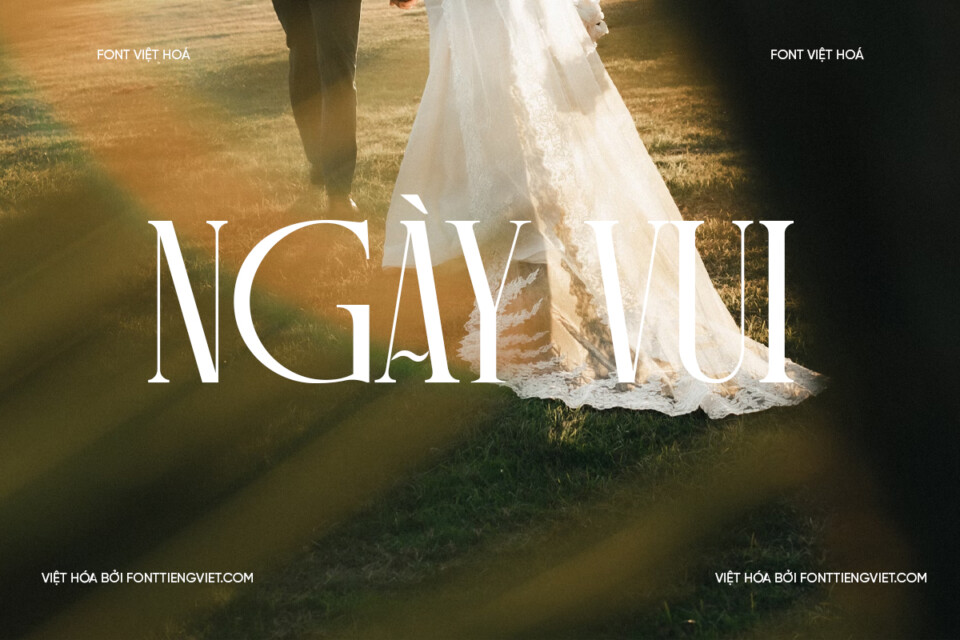
Font Việt hóa 1FTV VIP Camiro
Giới thiệu về Font Việt hóa 1FTV VIP Camiro trong thiết kế đồ họa
Trong thế giới thiết kế hiện đại, việc tìm kiếm một bộ font chữ vừa mang tính thẩm mỹ cao vừa hỗ trợ đầy đủ tiếng Việt là điều vô cùng quan trọng đối với các nhà sáng tạo. Font Việt hóa 1FTV VIP Camiro nổi lên như một lựa chọn hàng đầu nhờ sự kết hợp hoàn hảo giữa nét vẽ thanh thoát và cấu trúc hiện đại. Đây là bộ font được tinh chỉnh kỹ lưỡng để phù hợp với bảng mã Unicode, giúp người dùng dễ dàng gõ tiếng Việt mà không lo lỗi hiển thị. Khi bạn bắt đầu một dự án mới, việc lựa chọn Font Miễn Phí chất lượng như 1FTV VIP Camiro sẽ giúp nâng tầm giá trị thương hiệu và tạo ấn tượng mạnh mẽ với người xem ngay từ cái nhìn đầu tiên. Bộ font này không chỉ dừng lại ở các đường nét cơ bản mà còn chứa đựng tâm huyết của người việt hóa, đảm bảo từng dấu câu và ký tự đặc trưng của ngôn ngữ Việt đều được hiển thị một cách tự nhiên và hài hòa nhất.
Những đặc điểm nổi bật của Font Việt hóa 1FTV VIP Camiro
Phong cách thiết kế sang trọng và đa dụng
Một trong những điểm khiến Font Việt hóa 1FTV VIP Camiro trở nên khác biệt chính là phong cách thiết kế tinh tế. Các đường nét được tạo hình với độ tương phản nhẹ nhàng, tạo cảm giác vừa cổ điển vừa mang hơi thở của thời đại. Điều này cho phép bộ font ứng dụng linh hoạt trong nhiều lĩnh vực khác nhau như thiết kế logo, làm tiêu đề tạp chí, hay sáng tạo các ấn phẩm truyền thông trên mạng xã hội. Sự cân bằng giữa các khoảng cách chữ (kerning) giúp văn bản trở nên dễ đọc, mang lại trải nghiệm thị giác mượt mà cho độc giả.
Khả năng tương thích và tính ứng dụng cao
Không chỉ dừng lại ở vẻ bề ngoài, bộ font này còn có khả năng tương thích tuyệt vời với các phần mềm đồ họa phổ biến như Adobe Photoshop, Illustrator hay Canva. Dù bạn là một designer chuyên nghiệp hay chỉ là học sinh đang tập làm quen với thiết kế, 1FTV VIP Camiro đều rất dễ dàng để cài đặt và sử dụng. Đặc biệt, bộ font này cực kỳ phù hợp cho các chủ đề về thời trang, làm đẹp, thiệp cưới hoặc các bìa sách cần sự lãng mạn và bay bổng. Từng ký tự trong bộ font đều được trau chuốt để giữ được bản sắc riêng mà không làm mất đi tính chuyên nghiệp tổng thể của tác phẩm.
Hướng dẫn sử dụng và tối ưu Font Việt hóa 1FTV VIP Camiro
Lưu ý khi lựa chọn font chữ cho dự án
Khi sử dụng Font Việt hóa 1FTV VIP Camiro, bạn nên chú ý đến việc kết hợp với các font chữ không chân (Sans-serif) khác để tạo sự đối trọng. Việc sử dụng quá nhiều font trang trí trong một bản thiết kế có thể gây rối mắt, vì vậy hãy dùng 1FTV VIP Camiro làm điểm nhấn cho các tiêu đề lớn hoặc các câu trích dẫn quan trọng. Ngoài ra, việc điều chỉnh kích thước chữ và khoảng cách dòng hợp lý sẽ giúp phát huy tối đa vẻ đẹp của bộ font này trên cả nền tảng in ấn và hiển thị kỹ thuật số.
Kết luận về giá trị của bộ Font Việt hóa 1FTV VIP Camiro